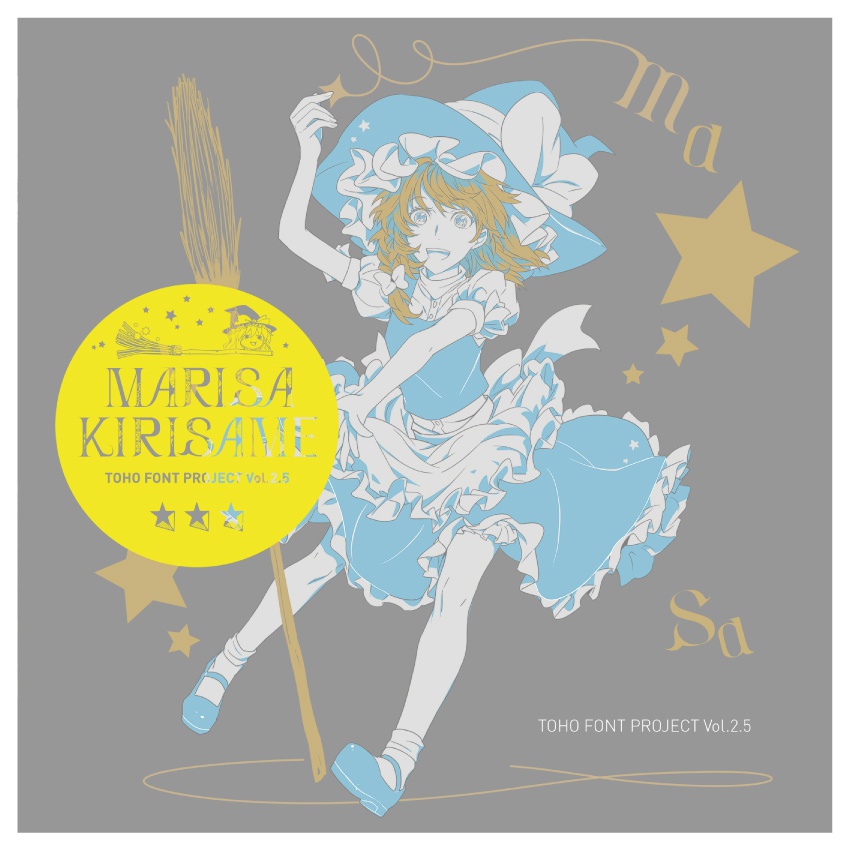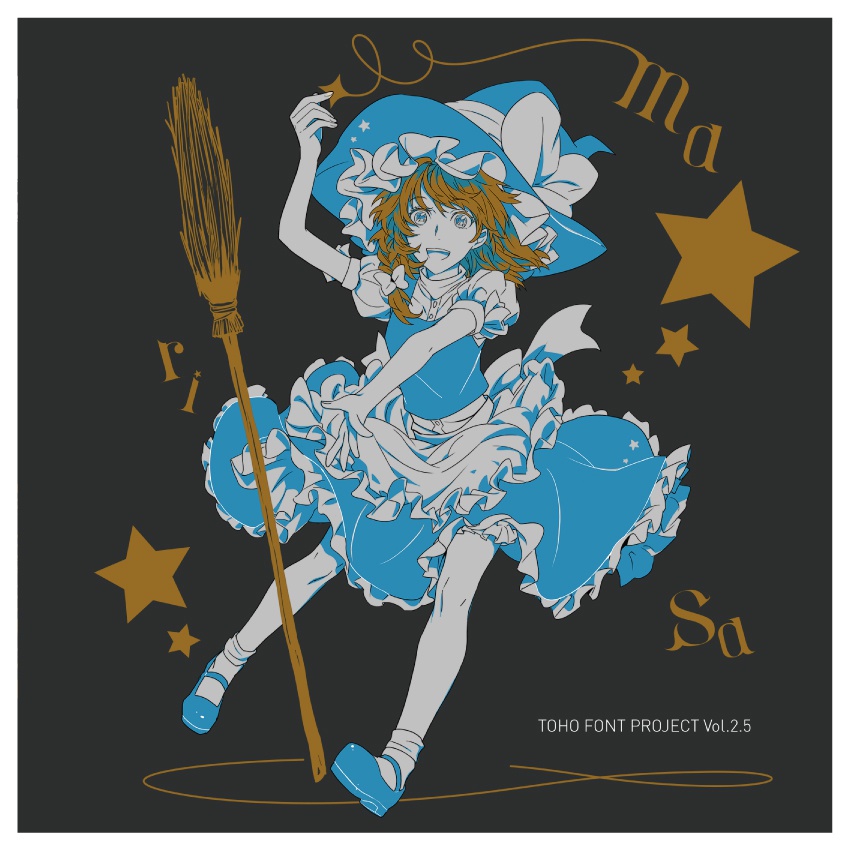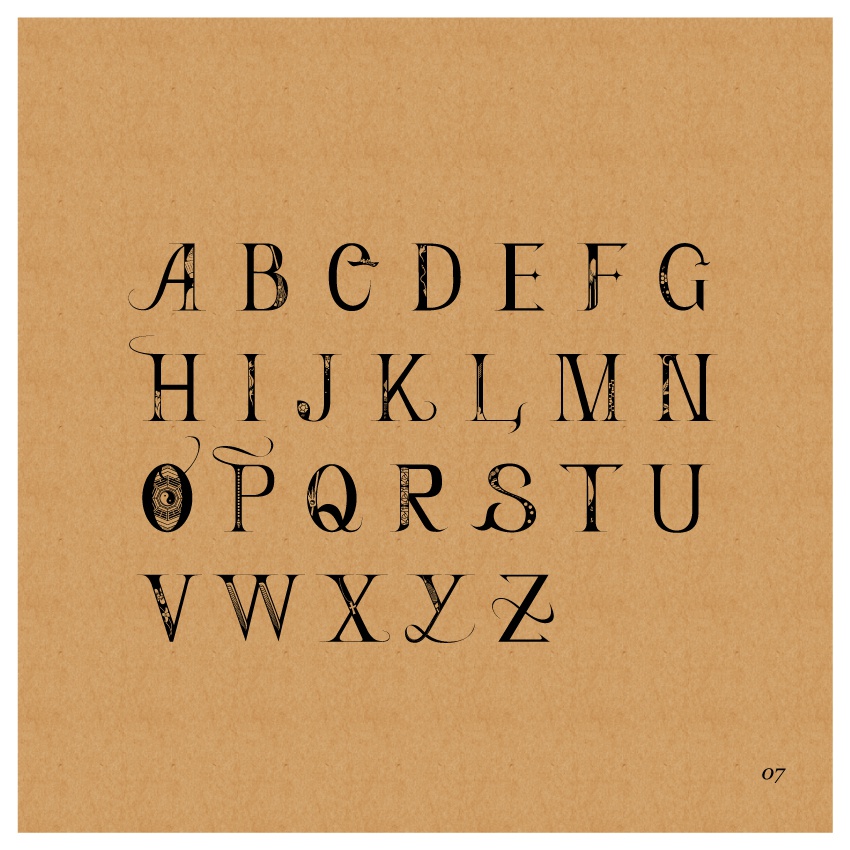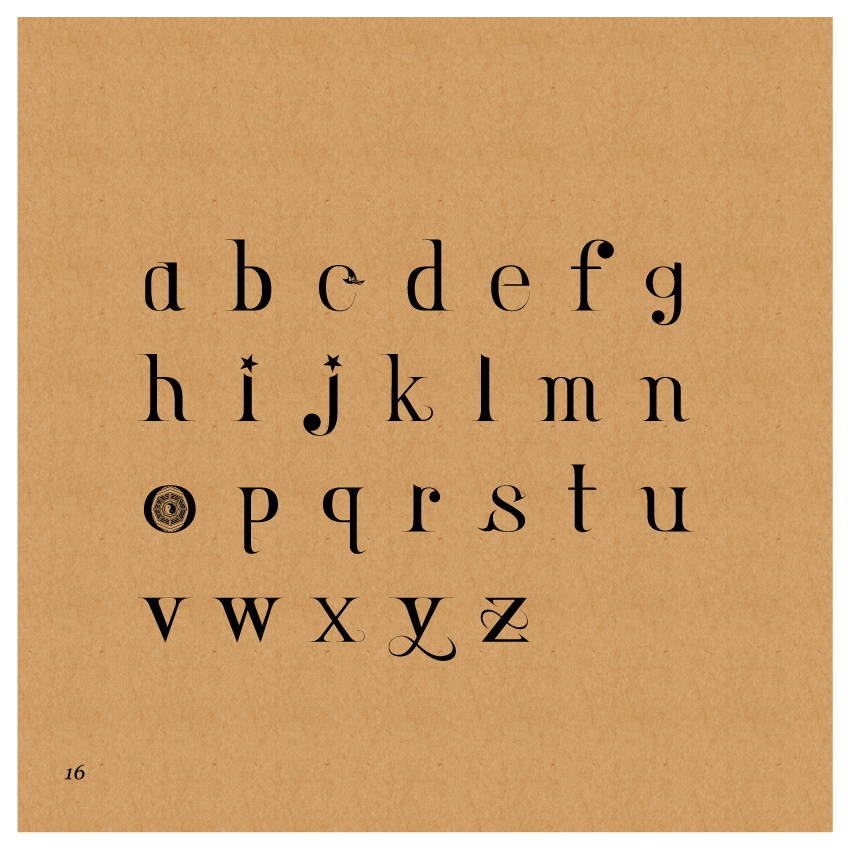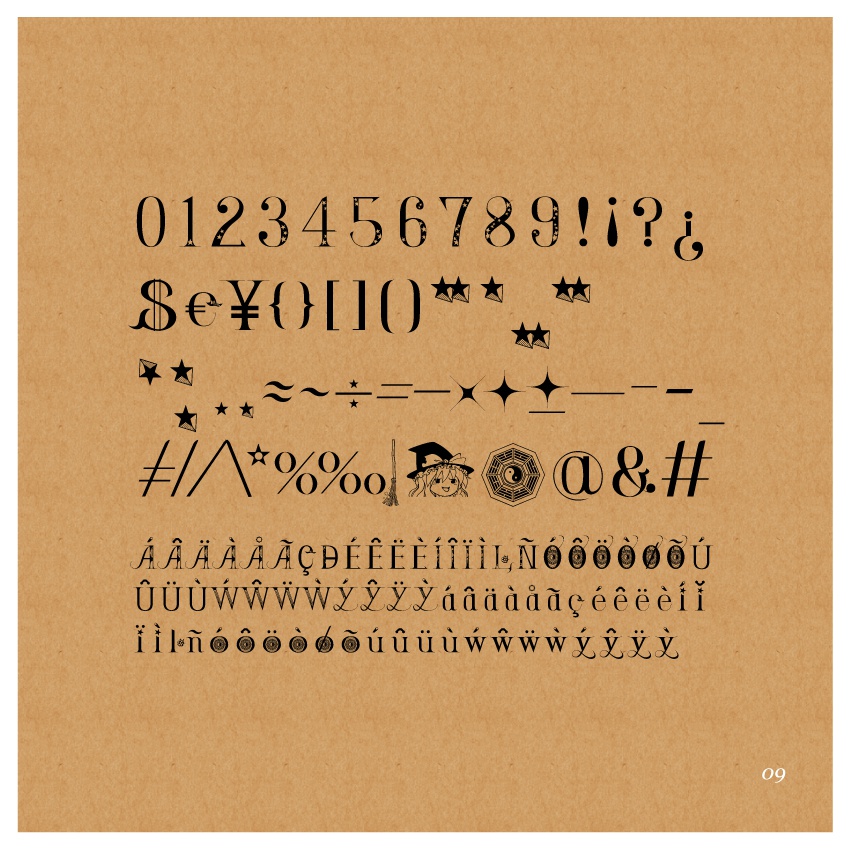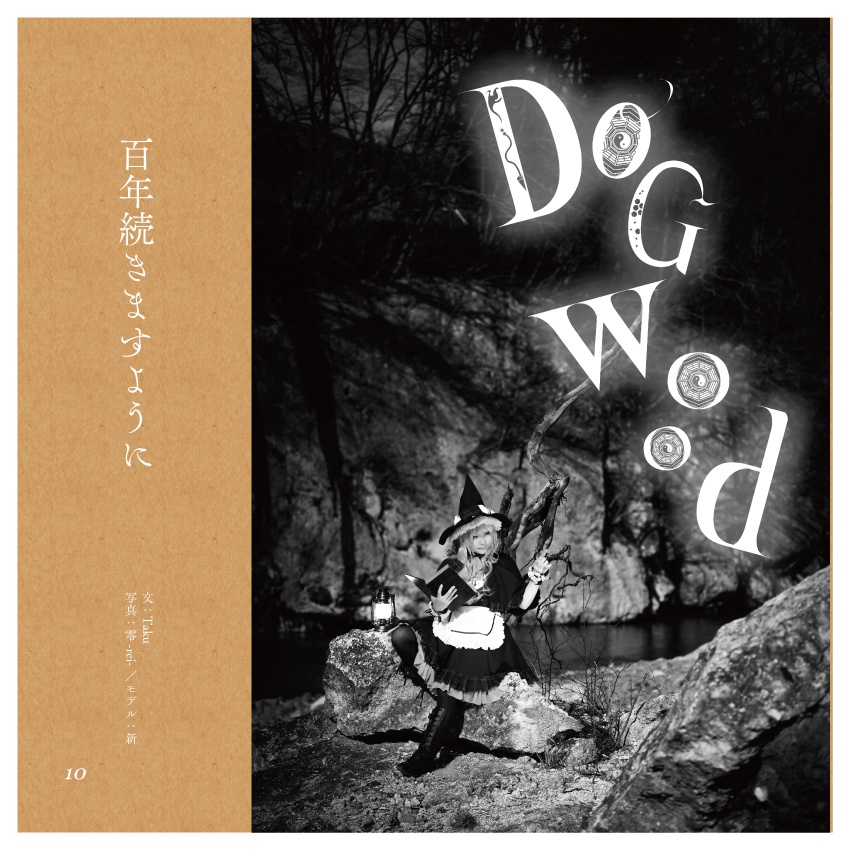
TOHO FONT PROJECT Vol.2.5 霧雨魔理沙
FONT付きBOOK 擬人化ならぬキャラクター書体化本 霧雨魔理沙UPDATEのオリジナル書体をダウンロードできる。 コスプレ名刺やデザインを作りたい人にオススメです。WEBFONTとしても使用できるのでウェブサイトや印刷物といった個人・商業に関係なくお使い頂けます。 下記から試し打ちもできます。 http://font.heartx.info/r12/ ・制作秘話 ・コスプレ写真の使用例 ・FONTデータ&ダウンロードコード (OPEN TYPE) ・Web font用データ一式 ipadなどをお持ちの方は sidebooksなどのAPPに入れて見ると本を見るように捗ります。 http://font.heartx.info/